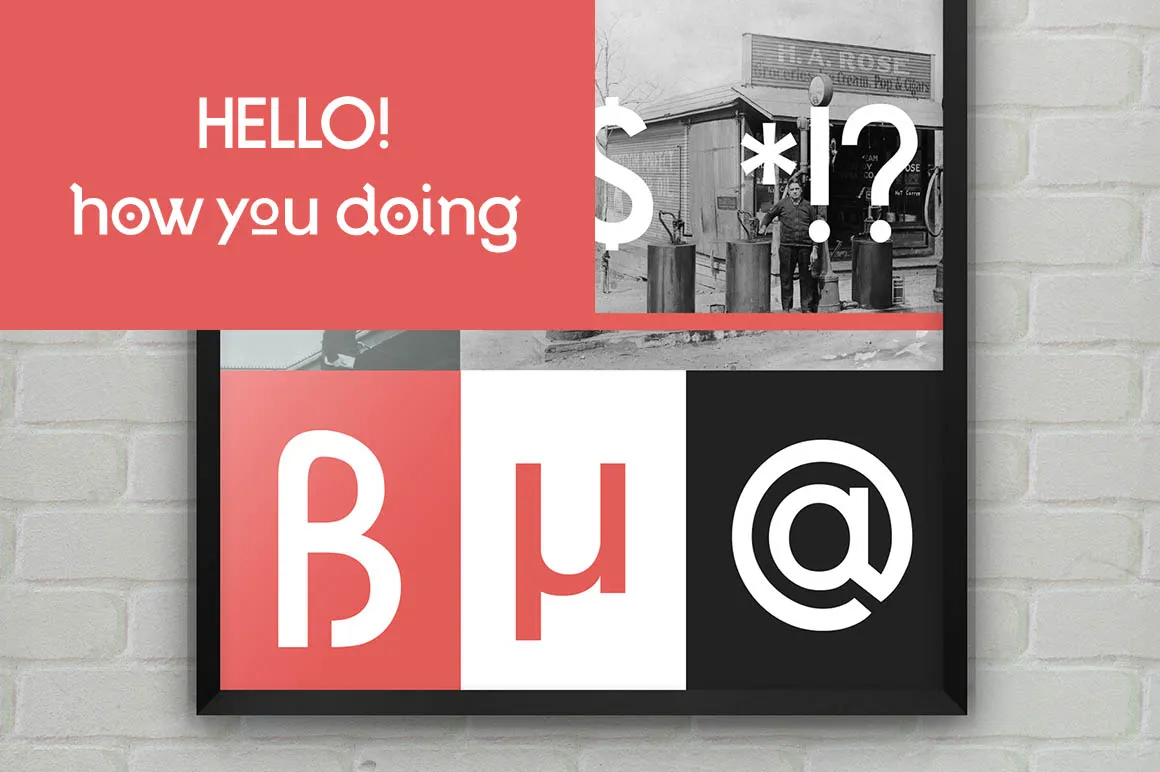
A DeLaFuente Font é uma elegante tipografia sans-serif criada pelo designer Alex de la Fuente. Esta fonte traz um ar moderno e limpo que se adequa perfeitamente aos novos trabalhos gráficos contemporâneos. Seja para criar sua próxima peça de arte ou design digital, a DeLaFuente Font oferece uma aparição fresca e funcional sem perder o toque personalizado de seu criador. Essencialmente versátil e moderna, ela é um grande aliado para os designers em busca de uma fonte que se destaque na cena do design atual. Descarregue a sua cópia agora e desfrute da qualidade desta font customizada.